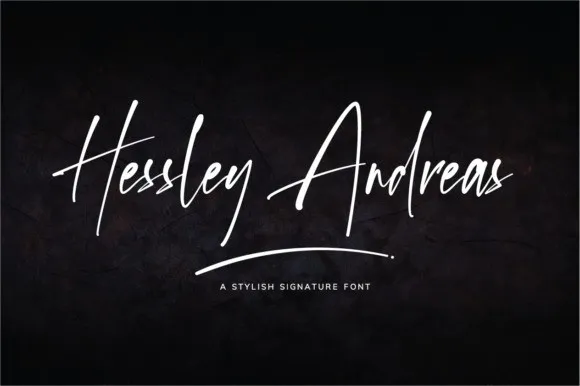
Hessley Andreas Script Font – Download Grátis
A Hessley Andreas Script é uma opção perfeita para quem busca um script elegante e moderno. Ela foi projetada com a intenção de oferecer uma sensação natural e fresca, sem perder seu charme elegante. Esta fonte vem com uma mistura única de estilo escrita por mão e tipográfico que proporciona uma aparência perfeita para qualquer projeto que requer o toque autêntico de uma assinatura manual. Para designers que buscam uma solução fácil e atraente, Hessley Andreas Script é um excelente complemento para seus trabalhos. Com seu estilo elegante e sua forma natural, ela oferece uma abordagem moderna e versátil que se destaca em projetos variados. Descubra o fascínio desta fonte cuidadosamente criada e conquiste um design único com Hessley Andreas Script.